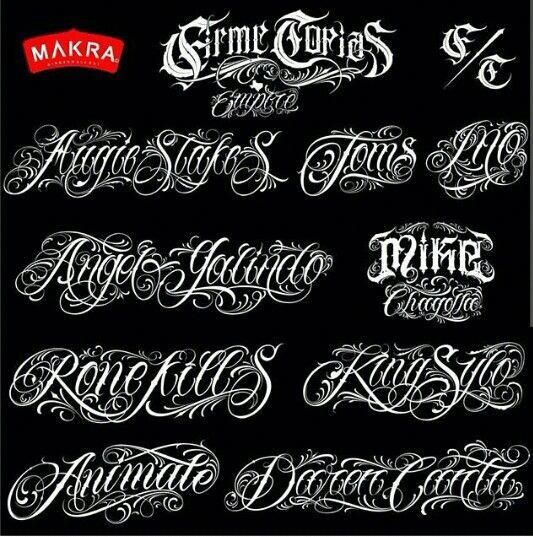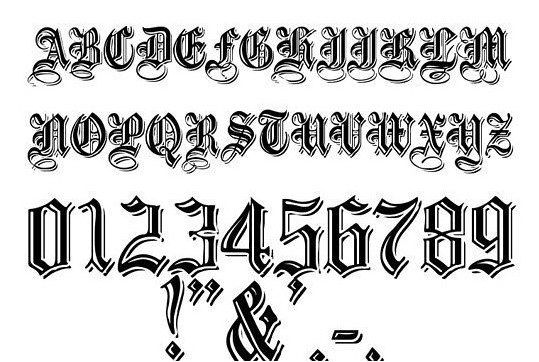
Лучшие шрифты для небольших татуировок – это не то, что вы найдете в Интернете
Маленькие татуировки – это наркотик, открывающий путь в мир тату-мастерства. Будь то ваша первая татуировка или маленький шаг к полному рукаву, маленькая татуировка может стать убийственным способом сделать татуировку. Маленькие татуировки несут в себе бесконечное количество значений, особенно для первой татуировки. Писать словами — это, очевидно, популярное занятие. Но как лучше всего татуировать эти маленькие буквы? Есть миллион и один тип шрифтов, с которыми вы могли бы работать, и с ураганом сенсорной перегрузки, которым является Pinterest, сложно сузить круг.
Я поболтал с несколькими тату-мастерами, которые предложили мне свой опыт.
Консенсус? Что ж, ваш типичный «шрифт» может оказаться не самым лучшим вариантом. Вот почему.
«Многие используют рукописные или классические шрифты для татуировок, — говорит Лало Юнда из Lalo Tattoos в Нью-Йорке. «Но компьютерные скучны. У них нет характера». Так что да, они работают, но они не супер оригинальны. Вместо обычного шрифта Юнда рекомендует использовать для слов что-то более персонализированное.
«Лучший шрифт — это почерк человека — почерк клиента», — сказал он. «Если вы просто хотите немного личного заявления, ваш собственный почерк хорош».
Это высший признак оригинальности: нет двух одинаковых почерков. Становится ли это более персонализированным?
Джули Болин, тату-мастер из American Electric в Лос-Анджелесе, также рекомендует рукописный маршрут.
«Рукопись и скоропись — это то, к чему я всегда стараюсь призывать людей», — сказала она. «Стандартные шрифты просто не обеспечивают изящных татуировок — особенно потому, что эти компьютерные шрифты трудно воспроизвести человеку».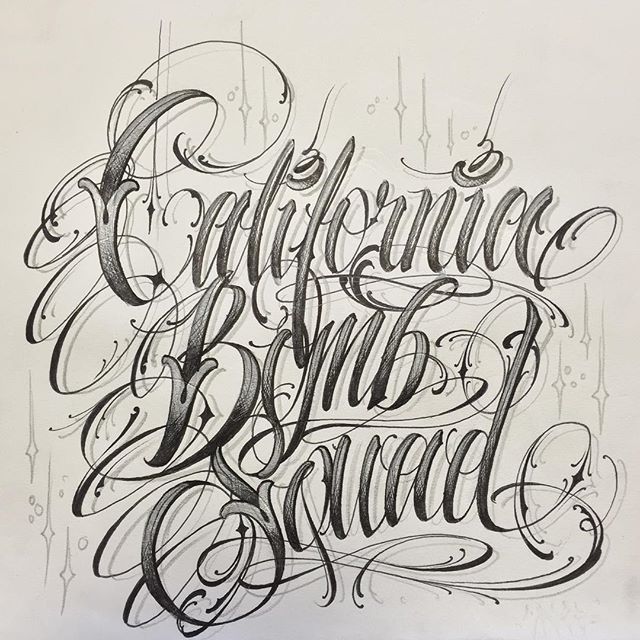
«Взгляд сразу же устремляется к изъяну», — сказала она. «Все, что имеет ровные надписи, начинает выглядеть странно, когда ваша кожа стареет или обвисает».
Когда татуировка заживает, чернила выходят за пределы линий. Поэтому, если линии шрифта расположены слишком близко друг к другу, они могут стереться друг с другом и сделать татуировку неразборчивой.
Знаменитый художник-татуировщик Кит “Bang Bang” Маккарди из Bang Bang Tattoos в Нью-Йорке знает кое-что о маленьких татуировках: он вдохновитель знаменитой татуировки Кары Делевинь в виде львиного пальца. Он сделал татуировку Джастину Биберу в самолете. Совсем недавно он сделал татуировку Кайли Дженнер, которая в ответ сделала ему татуировку. Довольно хардкорная штука.
Маккарди сказал мне, что он использует специальные шрифты для своих клиентов. Вместо того, чтобы прокручивать стандартные шрифты Word, он настраивает надписи, чтобы татуировка излучала оригинальность. Художник показывает клиенту примеры шрифтов, и вместе они разбивают его на то, что нравится клиенту и что лучше всего подходит для места татуировки и размера.
Затем Маккарди возьмет этот более стандартный шрифт в PhotoShop, чтобы манипулировать им. Таким образом, даже если двум клиентам сначала нравится один и тот же шрифт, то, что в конечном итоге наносится татуировкой, у обоих людей разное.
Однако Маккарди говорит, что если бы у него было , чтобы выбрать один конкретный шрифт, это был бы Times New Roman: простой и классический. Но больше, чем один шрифт, он рекомендует выбрать что-то не слишком плотное или слишком жирное.
Расположение татуировки также влияет на то, какие шрифты работают хорошо. Все художники согласились с тем, что гибкие, подвижные части вашего тела — например, пальцы, ступни, локти и колени — труднее татуировать и менее способны удерживать острую линию с течением времени. И опять же, нет единого шрифта или начертания, которые работают лучше всего — все зависит от того, что вы хотите и что рекомендует ваш художник. Серьезно, тот, кто рисует вас, сможет сделать идеальный вызов для вашего конкретного произведения искусства.
Лучшее блюдо на вынос? Быть гибким. Юнда особо подчеркивает это: у вас больше шансов уйти с убийственной татуировкой, которую вы полюбите навсегда, если вы готовы слушать экспертов и экспериментировать с размещением, шрифтом и размером.
«Идите с открытой душой. Скажите своему артисту, что вы хотите, но будьте открытыми», — говорит Юнда. «Проведите исследование [о художниках и татуировках]. Например, если бы вы собирались сделать операцию на носу, вы бы не пошли просто на это. Так же должно быть и с татуировками. Маленькая татуировка, большая татуировка — к каждой татуировке следует относиться с уважением, как со стороны художника, так и человека, который ее делает». Правда.
Тату-шрифты
923 крутых скрипта, 37 полных алфавитов ручной работы.
Шрифты для татуировки ручной работы, множество различных стилей: линейные и минималистичные шрифты, детский почерк, вертикальные шрифты, элегантный почерк, пишущая машинка, заглавные буквы и многое другое.